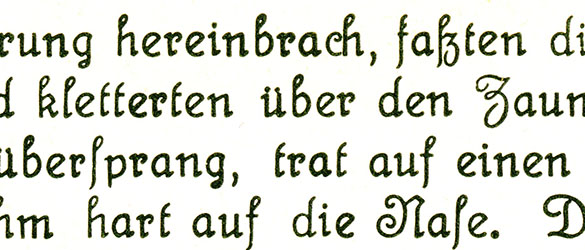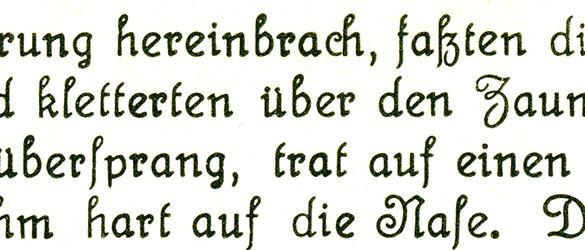
Font auf alter Postkartenserie
ich möchte gerne die Rückseiten von alten Postkarten nachbauen.
Die Baltimore Type Foundry hat später eine eigene Version
der »Sensation« unter dem Namen »Elegante« herausgebracht.
Eventuell wirst du unter dieser Bezeichnung fündig...
Korrektur zu meiner ersten Antwort: Ursprünglich erschien
die Schrift 1913 bei Heinrich Hoffmeister in Leipzig. Stempel hat
diese Gießerei später übernommen (siehe Bauer, Friedrich:
»Die Schriftgießerei im Jahre 1913«, in: Archiv für Buchgewerbe,
Leipzig, 1913).